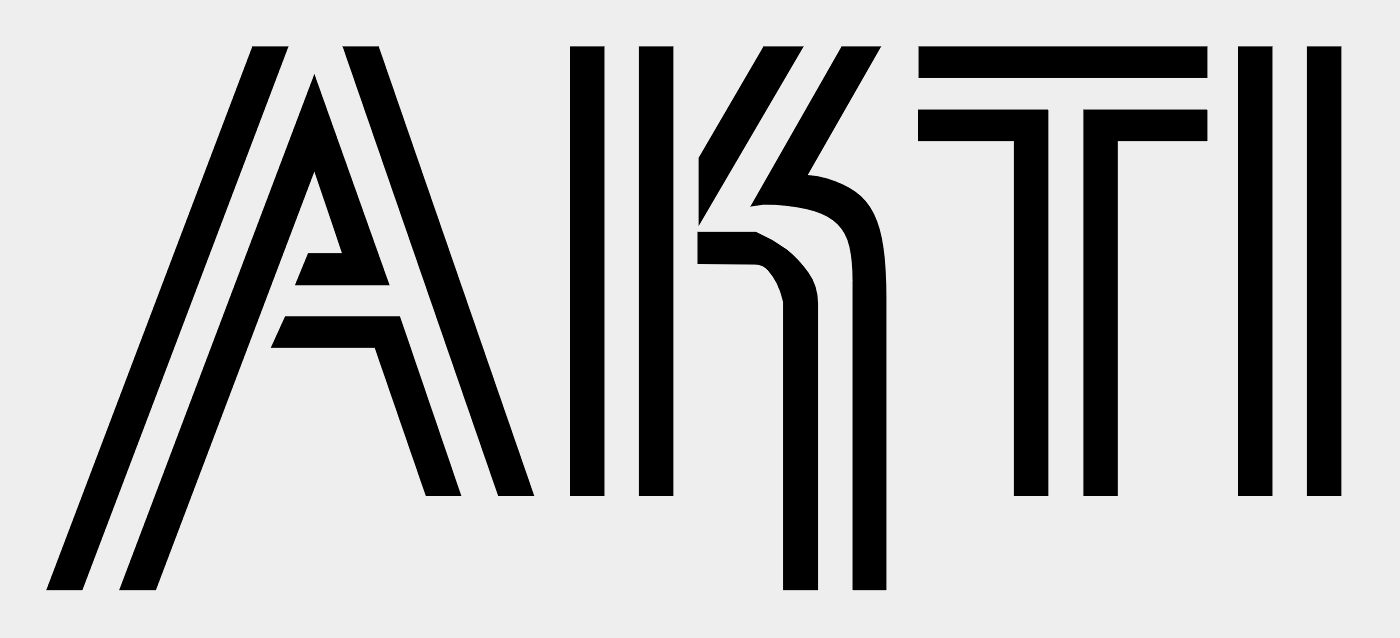
Schrift Typ Art Buchstabe Doppelt (Akti)
Von einer Alten (sehr alten Vereinsseite) müsste ich das Logo nachbauen.
Leider hat nur das mini Logo auf der Webseite die Zeit überstanden.
Unter welchen begriff müsste ich suchen, das ich schriftarten mit Doppel Linen erhalte.
ähnlich:
Das K sieht handwerklich grauslich aus …
Ich vermute, dass da noch mehr Buchstaben als nur AKTI verwendet werden sollen und diese dann in mehreren Medien, daher ist neu zeichnen oft keine Alternative.